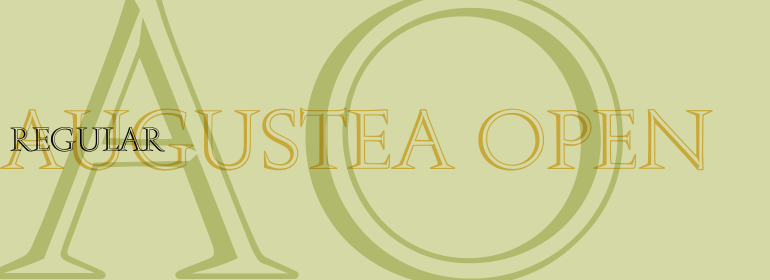
Augustea Open™
Augustea Open™,这款字体结构工整、笔画清晰,兼顾美观与易读性,适用于标题、正文、海报、包装、LOGO 等多种场景。字形优雅稳定,风格百搭耐看,适配日常排版与创意设计,让文字呈现更舒适、更具质感。Augustea Open™一笔一画,皆是细节,以均衡的比例、流畅的线条打造舒适视觉体验,字形端正大气,风格简约现代。无论是商业设计、品牌宣传还是日常排版,都能轻松驾驭,让文字更有格调与力量。Augustea Open™字体下载。